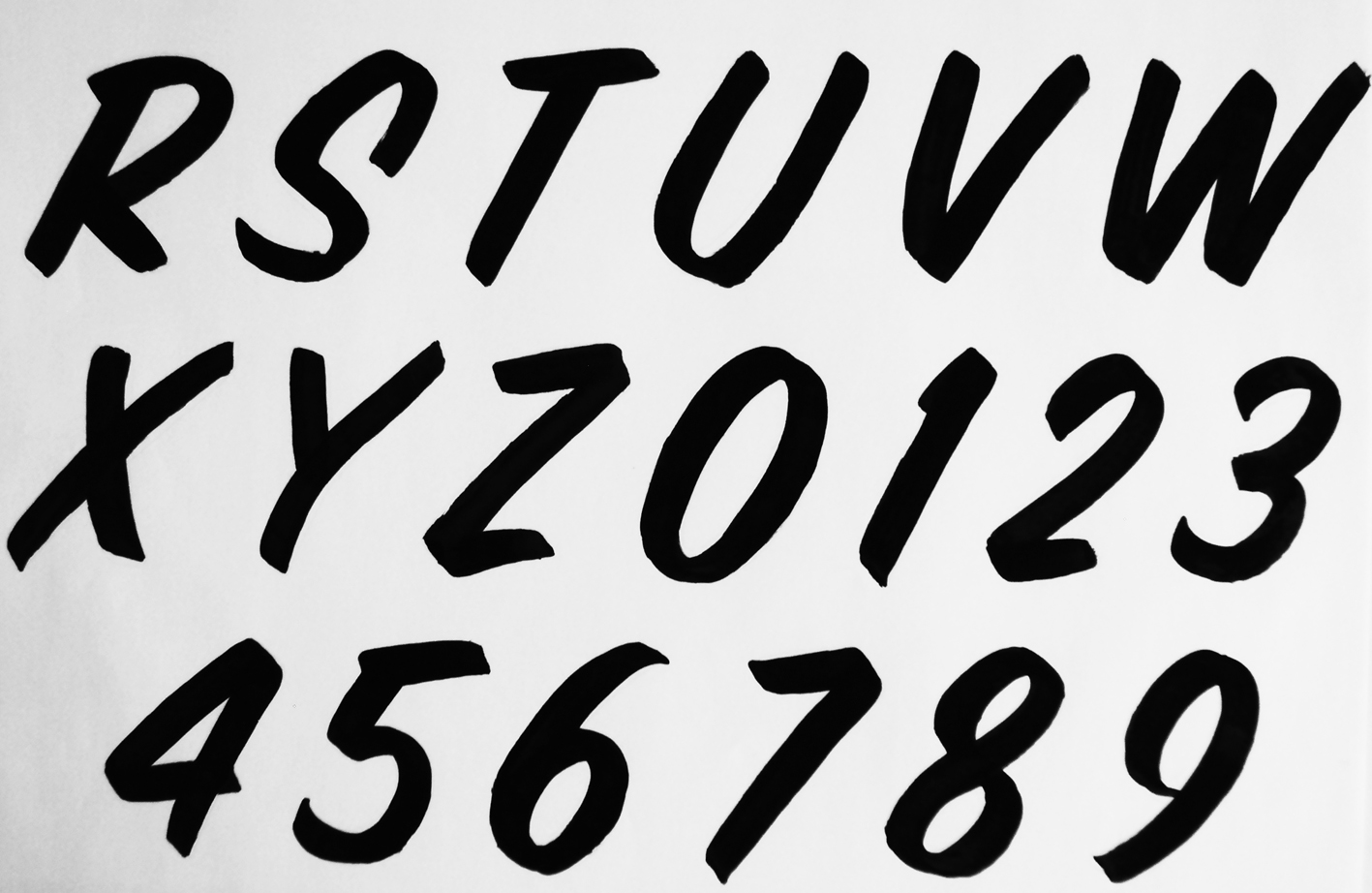
Il y a 10 jours environ, j'ai participé à un stage proposé par Apex avec
Benjamin Grange qui est peintre en lettres et qui a son atelier à Nancy "
Studio Pinceaux ".
Nous avons commencé par les gammes (verticales, horizontales, courbes et obliques).
Il fallait faire attention à la dilution de la peinture (white spirit, la salle embaumait...), à l'entame et la fin de chaque trace, à ne pas trop charger le pinceau et à bien appuyer afin d'obtenir une trace régulière et bien large !
Premiers traits > peinture trop épaisse
Les " dégoulinures " sont dues à un pinceau trop chargé ou à de la peinture trop fluide...
Test de quelques lettres bâtons, et même calligraphiées (ce n'était pas demandé... j'ai voulu tout de même voulu essayer) !
La peinture sèche assez lentement...
Puis, Benjamin nous a proposé de travailler la lettre Casual (exemple ci-dessous) :
Voici ce que j'ai fait (sur photocopies, juste le contour des lettres, fournies par Benjamin pour nous faciliter la tâche).
Puis en dessinant, au préalable, le contour des lettres pour former des mots.
Il est difficile de rester toujours bien régulier en ce qui concerne l'épaisseur du trait...
Les courbes et les proportions de certaines lettres sont à revoir mais pour un début c'est plutôt pas mal !
Par contre pour ce qui suit, j'ai gardé le type de lettre mais j'ai voulu apporter un peu de dynamisme (comme avec les versales). Une vision plus calligraphique...
et donc non " validée " par Benjamin !!
Voyant que nous nous en sortions pas trop mal, Il nous a proposé de faire des lettres ou mots avec de la profondeur (perspective, ombre...)
| lettrage issu d'un livre allemand apporté part Elisabeth |
| lettre en creux, sur papier transparent, non terminé |